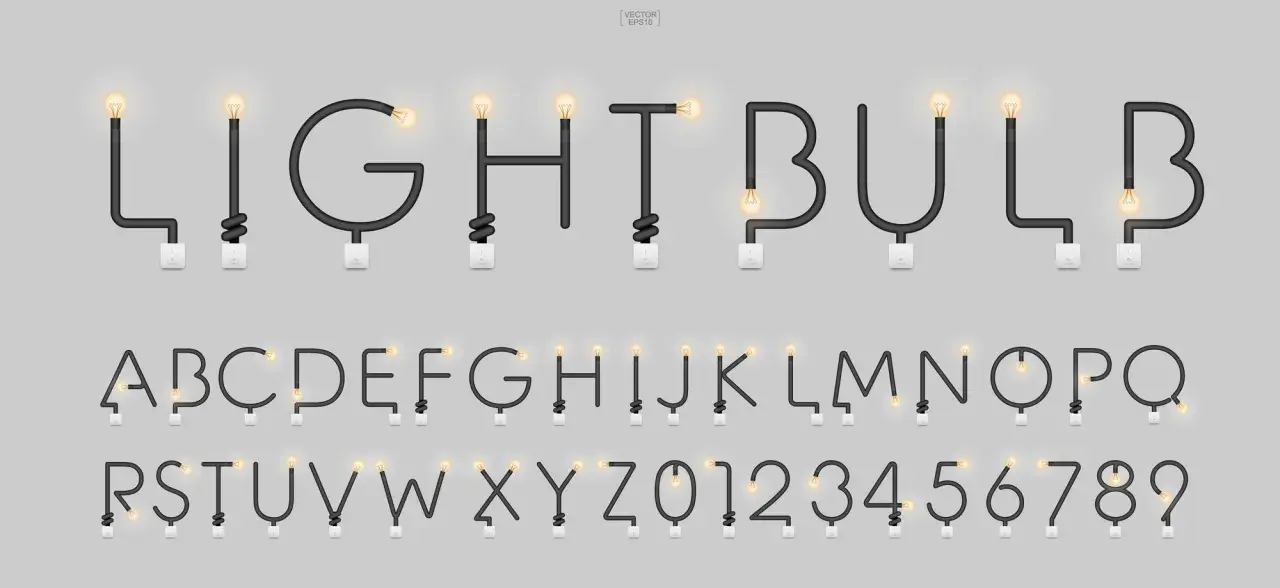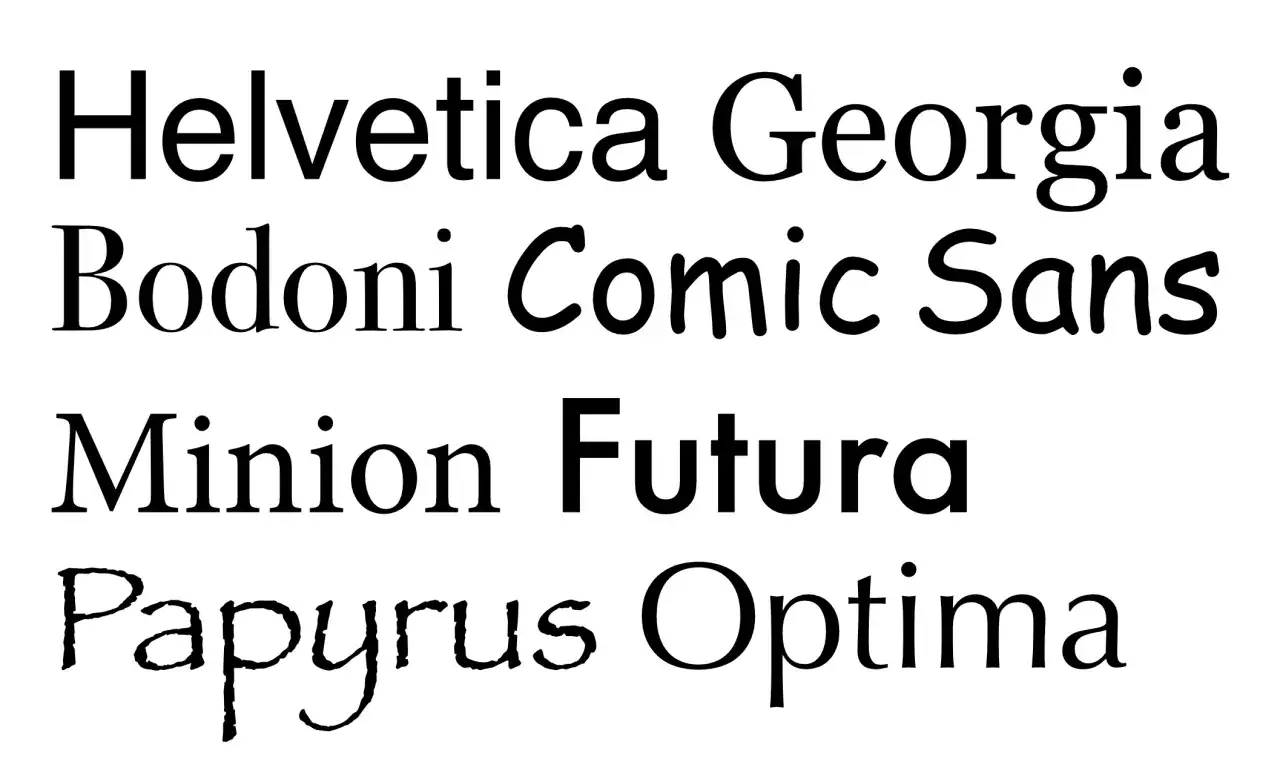
Krój pisma, font a czcionka - Czym się różnią i jak wybrać mądrze?
Litery i cyfry uformowane z czarnego kabla, z żarówkami i włącznikami. Unikalny font, który rozświetla alfabet.
W typografii liczy się nie tylko to, co jest napisane, ale też jak wygląda litera, jej rytm i czytelność na ekranie, szyldzie czy ulotce. Różnica między czcionką, fontem i krojem pisma wydaje się drobiazgiem, ale w praktyce pomaga lepiej dobrać typografię do marki, reklamy i treści użytkowych. W tym artykule rozkładam ten temat na proste przykłady i pokazuję, jak nie pomylić pojęć, kiedy przygotowujesz projekt dla lokalnego biznesu.
Czcionka a font to nie to samo, choć w codziennej rozmowie te słowa często się mieszają
• Krój pisma to projekt liter, czyli ich wspólny wygląd i charakter.
• Font to konkretna odmiana tego projektu, np. Regular, Bold albo Italic, albo plik zawierający taką odmianę.
• Czcionka w ścisłym znaczeniu to drukarski nośnik z epoki składu ręcznego, a nie plik w komputerze.
• W rozmowach potocznych „czcionka” bywa używana szerzej, ale w typografii lepiej mówić precyzyjnie.
• Przy reklamie lokalnego biznesu ważniejsze od samej nazwy jest to, czy litery są czytelne, spójne i dobrze działają w małym oraz dużym formacie.
Co oznaczają te pojęcia w typografii
Najprościej myśleć o tym tak: krój pisma to sam projekt liter, a font to jego konkretna odmiana lub cyfrowa postać, którą wybierasz w programie. Czcionka w ścisłym, drukarskim sensie oznaczała metalowy nośnik do składu ręcznego, więc historycznie jest czymś innym niż plik w komputerze. To rozróżnienie porządkuje całą resztę terminów.
Pojęcie Co oznacza Przykład
Krój pisma Projekt wyglądu liter i znaków, czyli wspólny charakter całej rodziny. Garamond, Helvetica, Inter
Font Konkretna odmiana kroju albo jego cyfrowa postać, np. w wersji regular, bold czy italic. Inter Regular, Inter Bold, Inter Italic
Czcionka Historyczny, drukarski nośnik używany przy składzie ręcznym. Metalowy klocek z odbitką znaku
Glif Konkretny kształt pojedynczego znaku, np. litery „a” w konkretnej wersji. Ozdobna lub zwykła wersja tej samej litery
Ja zwykle zaczynam od pytania, czy ktoś mówi o projekcie liter, czy o konkretnej odmianie w rodzinie, bo to od razu pokazuje, co właściwie zmienia. W nowoczesnych narzędziach dochodzi jeszcze font wariacyjny, czyli jeden plik, który może obejmować wiele odmian, na przykład różne grubości i szerokości. Kiedy to rozumiesz, łatwiej zobaczyć, skąd bierze się całe zamieszanie z nazwami.
Dlaczego w polszczyźnie te słowa się mieszają
W polskiej codzienności te pojęcia zlały się ze sobą także dlatego, że dawne programy i tłumaczenia utrwaliły zwyczaj używania słowa „czcionka” tam, gdzie technicznie chodziło o font. W rozmowie o grafice większość osób rozumie taki skrót, ale w briefie, opisie projektu albo przy rozmowie z drukarnią zaczyna to wprowadzać niepotrzebny szum.
To dlatego wolę mówić precyzyjnie: krój pisma, gdy mówimy o projekcie, font, gdy chodzi o konkretną odmianę, i „czcionka” tylko wtedy, gdy naprawdę odnosimy się do historycznego znaczenia. Ta różnica nie jest pedantycznym detalem. Ona po prostu oszczędza czas, kiedy trzeba podjąć decyzję typograficzną bez domysłów. Teraz warto przejść z teorii do tego, co faktycznie widzisz w menu programu.
Helvetica, Bodoni, Minion, Papyrus, Georgia, Comic Sans, Futura, Optima – różne style czcionek i fontów.
Jak rozpoznać, co zmieniasz w programie
Najłatwiej zauważyć różnicę, kiedy spojrzysz na to, co dzieje się w edytorze tekstu albo programie graficznym. Jeśli zmieniasz z jednej rodziny na drugą, zmieniasz krój pisma. Jeśli przełączasz Regular na Bold albo Italic, wybierasz inną odmianę tego samego kroju. Jeśli zwiększasz rozmiar z 12 pt do 18 pt, zmieniasz stopień pisma, a nie sam font.
Co robisz Co to oznacza Efekt
Wybierasz Inter zamiast Georgia Zmieniasz krój pisma Inny charakter liter, inna osobowość tekstu
Przełączasz Regular na Bold Zmieniasz font lub odmianę w obrębie tej samej rodziny Grubsze kreski, mocniejszy akcent
Zwiększasz rozmiar tekstu Zmieniasz stopień pisma Litery są większe, ale projekt pozostaje ten sam
Regulujesz kerning Poprawiasz odstęp między konkretnymi parami liter Nagłówek wygląda czyściej i bardziej równo
W praktyce właśnie tu pojawia się najwięcej nieporozumień. Ktoś mówi „zmień czcionkę”, a naprawdę chce grubszego kroju, lepszych odstępów albo bardziej eleganckiej odmiany. Warto też pamiętać o trackingu, czyli równomiernym rozstawieniu wszystkich liter w tekście, bo to nie to samo co kerning. Ta różnica zaczyna mieć realne znaczenie, kiedy typografia pracuje na wizerunek firmy.
Dlaczego typografia ma znaczenie w reklamie lokalnej
Dla lokalnego biznesu typografia nie jest ozdobą z boku. Ona wpływa na to, czy klient odczyta ofertę, zapamięta markę i uzna ją za uporządkowaną. W praktyce widzę, że dobrze dobrany krój często robi większą różnicę niż kolejny marketingowy slogan, bo porządkuje komunikat już na poziomie pierwszego spojrzenia.